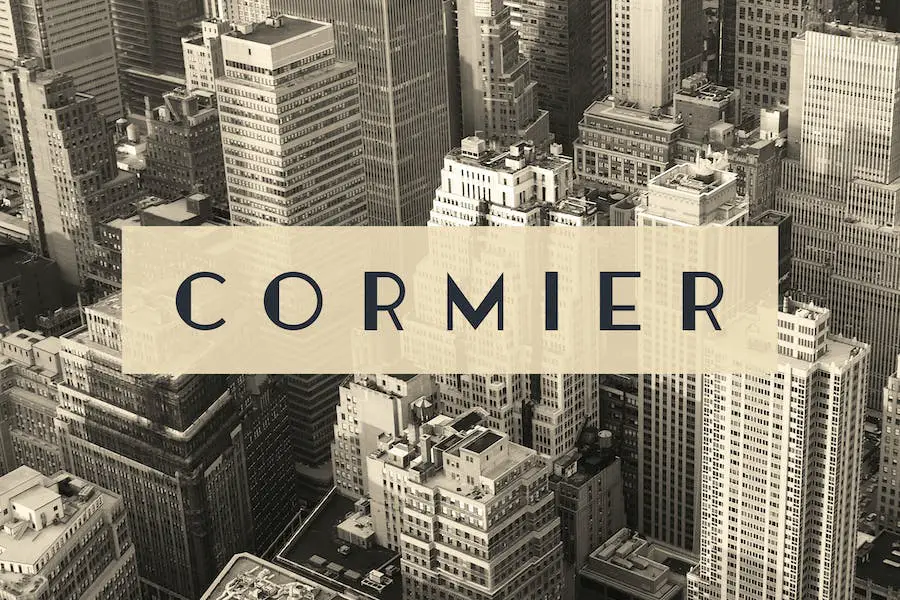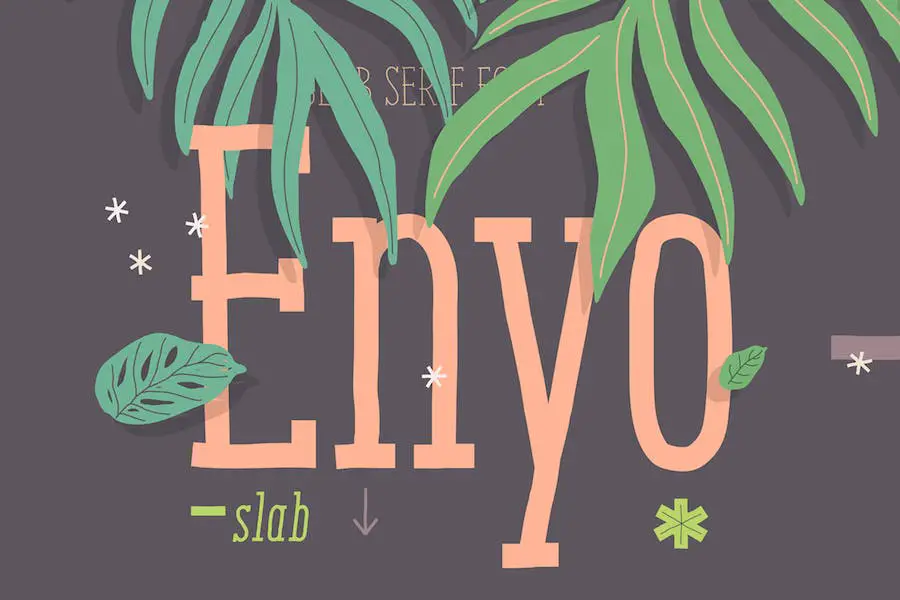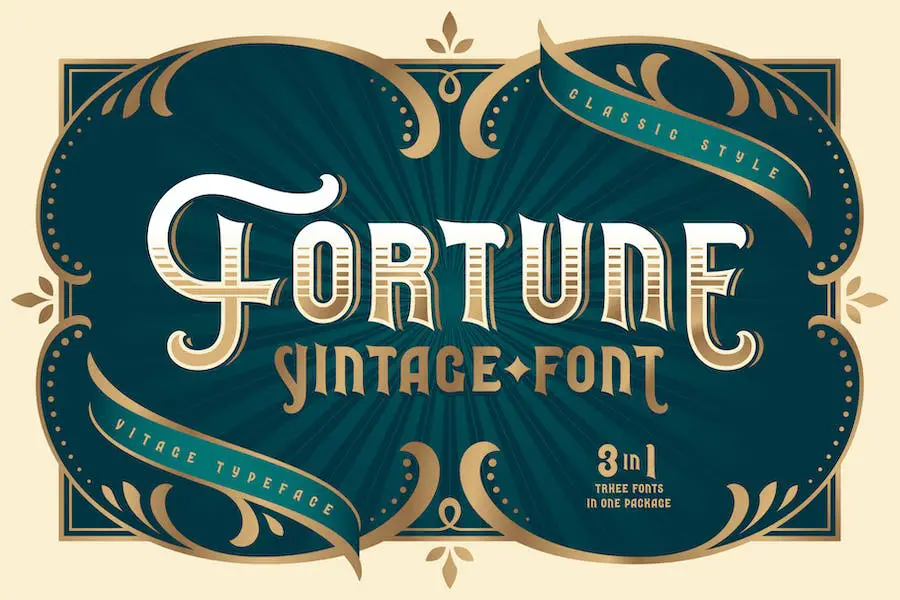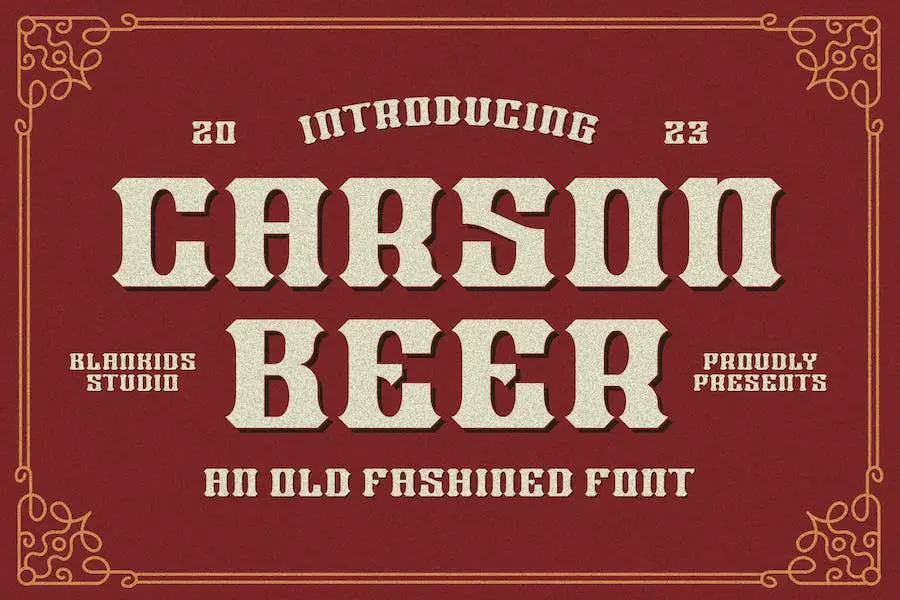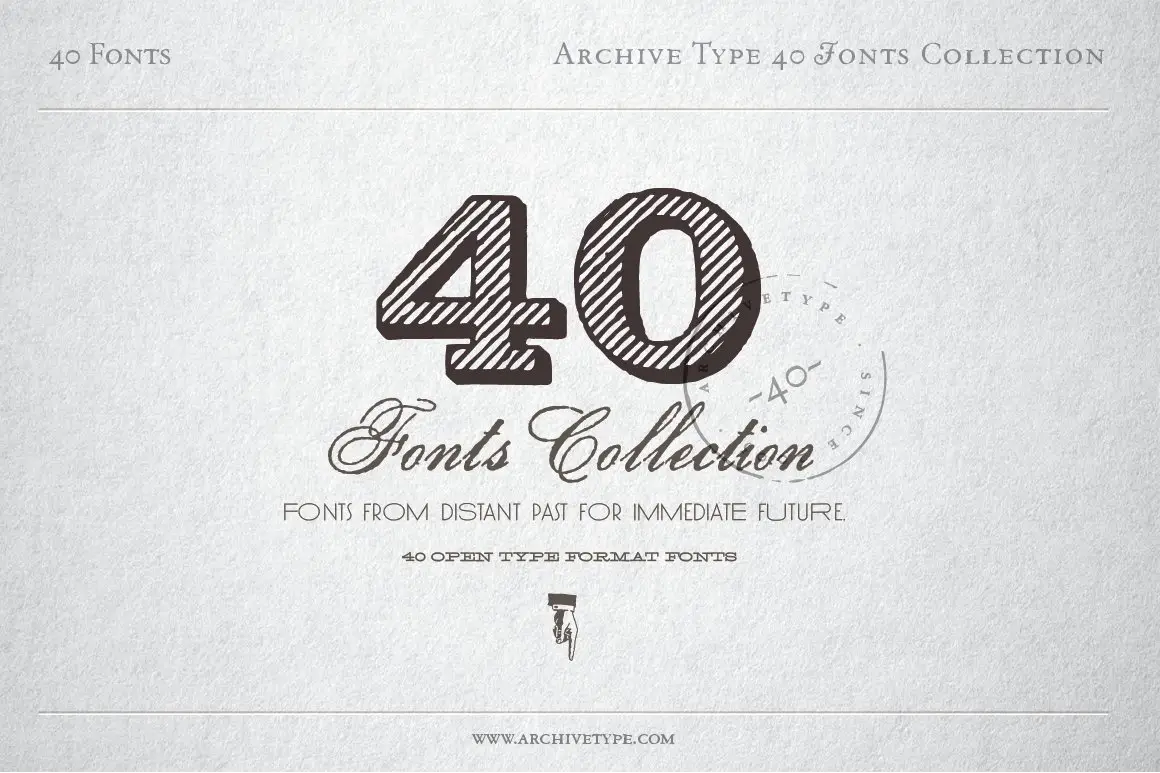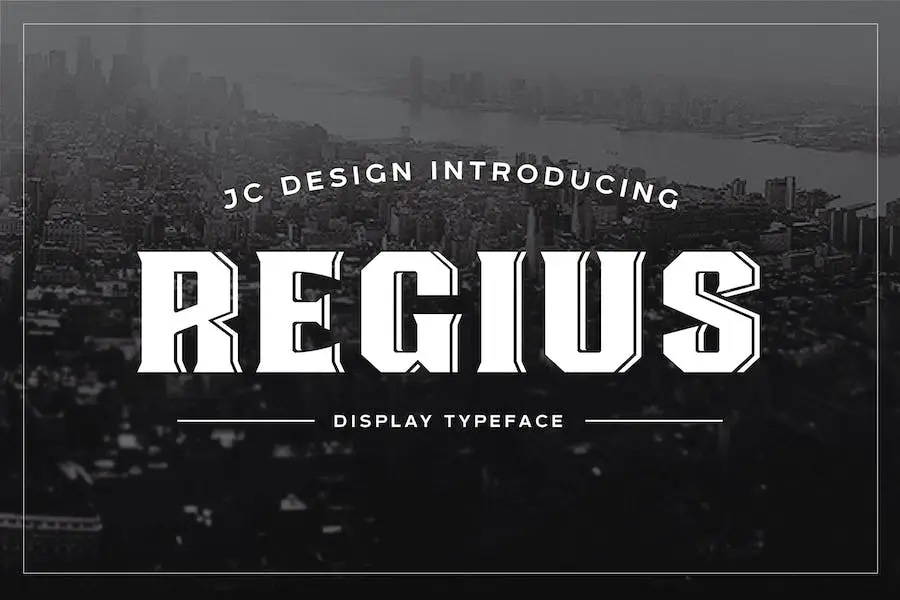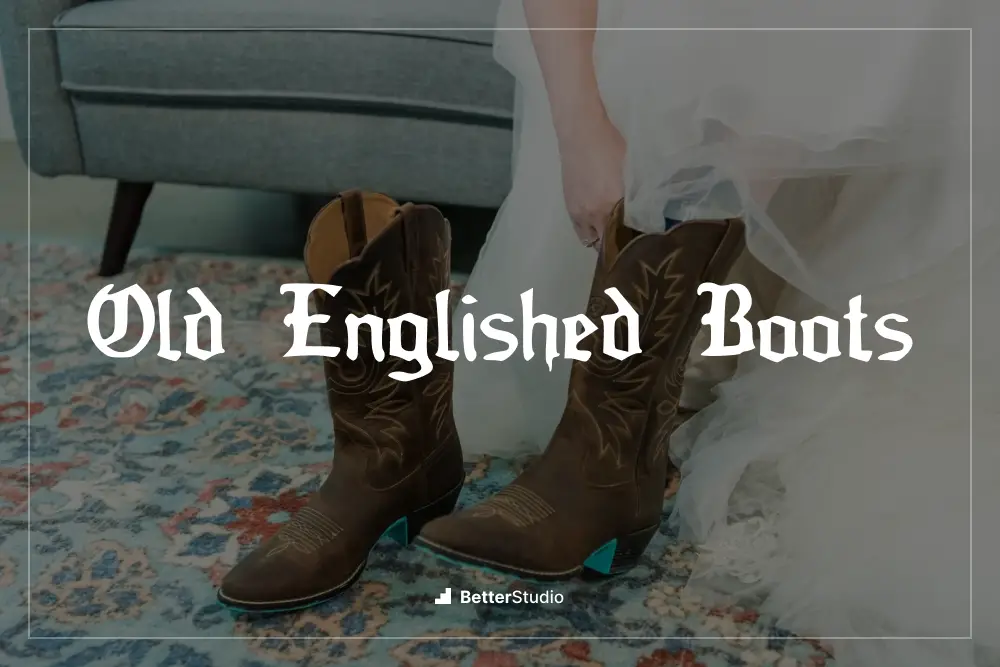
24 najlepsze staroangielskie czcionki ️ 2023 (bezpłatne i premium)
Opublikowany: 2023-05-21Czy jesteś grafikiem i szukasz idealnej starej angielskiej czcionki, aby ulepszyć projekt swojego projektu? Nie szukaj dalej! W tym artykule zebraliśmy listę 24 najlepszych starych angielskich czcionek, które z pewnością zrobią wrażenie.
Ponieważ typografia odgrywa istotną rolę w projektowaniu graficznym, wybór odpowiedniej czcionki może być trudny. Przy tak wielu dostępnych opcjach łatwo się zgubić. Dlatego przeprowadziliśmy dla Ciebie badania.
Nasz proces selekcji był obszerny i ocenialiśmy każdą czcionkę na podstawie kryteriów, takich jak popularność, wszechstronność i czytelność. Ten artykuł zawiera obszerny przewodnik po najlepszych starych czcionkach angielskich dostępnych obecnie.
W tym artykule przedstawimy Ci 24 najlepsze stare angielskie czcionki, które idealnie nadają się do każdego projektu. Niezależnie od tego, czy tworzysz logo, plakat czy projekt strony internetowej, nasza starannie dobrana oferta zapewni Ci wszystko.
Tak więc, bez zbędnych ceregieli, zanurzmy się w świat starych angielskich czcionek i znajdźmy idealną czcionkę do następnego projektu.
Najlepsze staroangielskie czcionki premium
Szukasz wysokiej jakości czcionek staroangielskich, które uatrakcyjnią Twoje projekty? Sprawdź nasze najlepsze typy, aby znaleźć najlepsze dostępne opcje premium. Nie przegap tych niezbędnych czcionek w zestawie narzędzi każdego grafika.
Wicked Olde English
Wicked Olde English to kolekcja staroangielskich czcionek Google, które są idealne dla grafików, którzy chcą dodać swoim projektom odrobinę uroku starego świata.
Te czcionki są idealne do tworzenia unikalnych i przyciągających wzrok projektów, od logo i wizytówek po plakaty i grafikę do mediów społecznościowych.
Starożytny
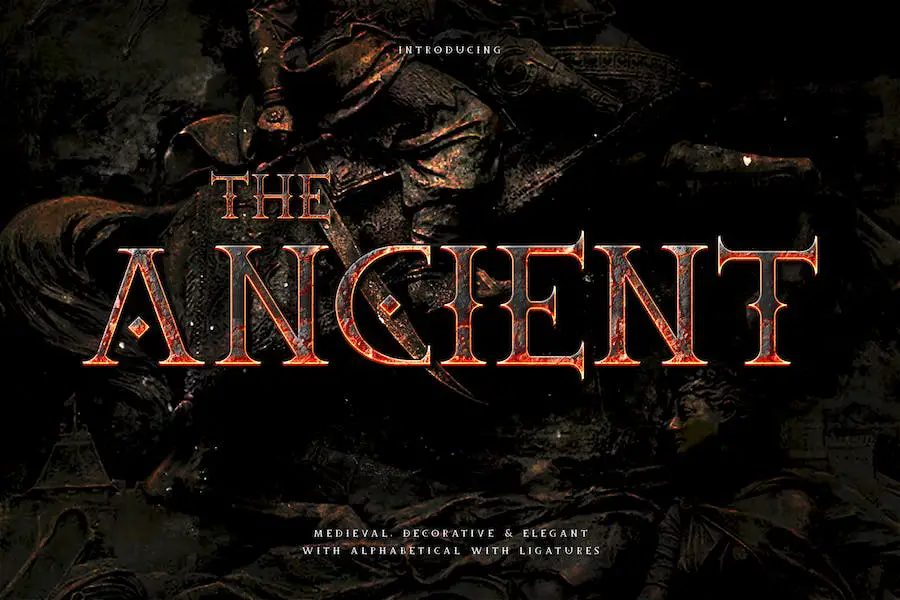
The Ancient to średniowieczna czcionka bez, która nadaje Twojemu projektowi styl vintage. To doskonały wybór dla grafików, którzy tworzą zaproszenia, banery, tytuły filmów, marki, wydarzenia, gry i nie tylko.
Jeśli szukasz czcionki, która pomoże Ci osiągnąć średniowieczną estetykę, The Ancient może być dla Ciebie idealną opcją.
Lore Nekromantea Hollow
Lore Nekromantea Hollow to piękna odręczna czcionka staroangielska, która została zaprojektowana do użytku w przeszłych, obecnych i przyszłych książkach, takich jak Tomy, Biblie i Grimoires.
Ta czcionka jest dostępna w 3 wariantach x 2 (zwykły i pusty) z różnymi dużymi literami: Nokturnia, Pandemonia i Nekromantea. Puste wersje mają celowo nierówną pracę linii i więcej punktów kontrolnych, dzięki czemu idealnie nadają się do nagłówków i wyświetlanego tekstu.
W przypadku nagłówków i wyświetlanego tekstu ta czcionka przyciągnie uwagę czytelników i doda odrobinę wyrafinowania Twojemu projektowi. Ogólnie rzecz biorąc, jeśli szukasz staroangielskich czcionek do programu Word, Lore Nekromantea Hollow to świetny wybór, który zapewnia wszechstronność i piękno w równym stopniu.
Chervels w starym stylu
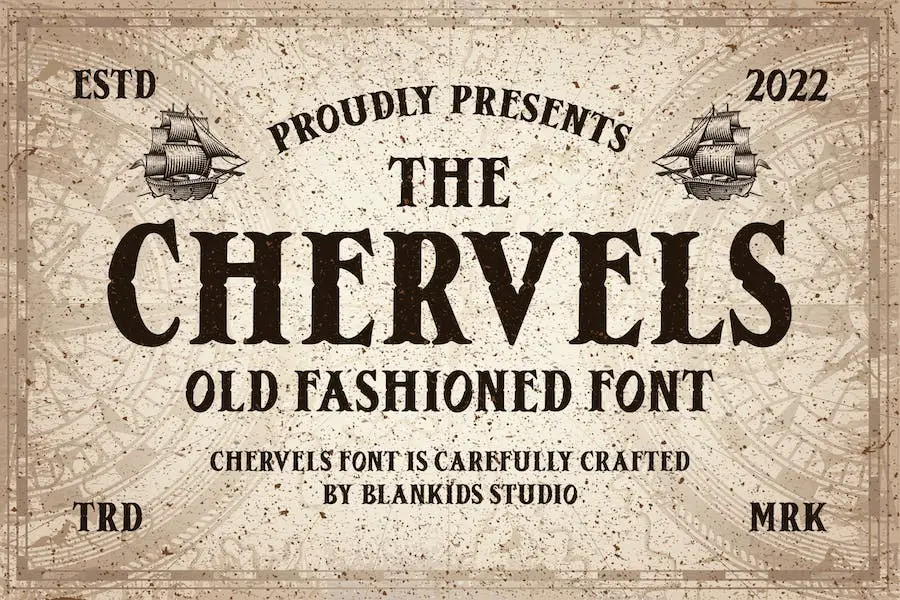
Chervels an old Fashioned to czcionka inspirowana stylem vintage, która dodaje figlarnego charakteru każdemu projektowi. Dzięki pięknie wykonanej estetyce ta czcionka jest idealnym wyborem do okładek książek, plakatów, opakowań, towarów, logo i nie tylko.
Czcionka Chervels, staroangielska, jest idealna do wykorzystania w projektach Canva, które wymagają czcionki staroangielskiej. Jest łatwy w użyciu i można go zastosować do różnych elementów projektu. Niezależnie od tego, czy projektujesz plakat, czy tworzysz logo, ta czcionka pomoże Ci osiągnąć pożądany styl vintage.
Blond
Blonde to nowoczesna rodzina czcionek typu blackletter, która obejmuje dwa style: ozdobną szeryfową teksturę i bezpłatną rotundę sans. Wyróżnia się na tle tradycyjnych staroangielskich czcionek opływowym wyglądem i stylem, zachowując jednocześnie stylizowane i czytelne cechy tego gatunku.
Ta rodzina czcionek wykorzystuje kąt obrysu 50° i zaokrąglone elementy, co nadaje jej wyjątkowy, organiczny wygląd.
Ogólnie rzecz biorąc, Blonde to świetny wybór dla każdego, kto szuka nowoczesnego podejścia do staroangielskich czcionek do projektów obwodów. Jego unikalny design i czytelność sprawiają, że jest to wyjątkowa opcja dla projektantów, którzy chcą przekazać poczucie tradycji i elegancji w swojej pracy.
Oryginały
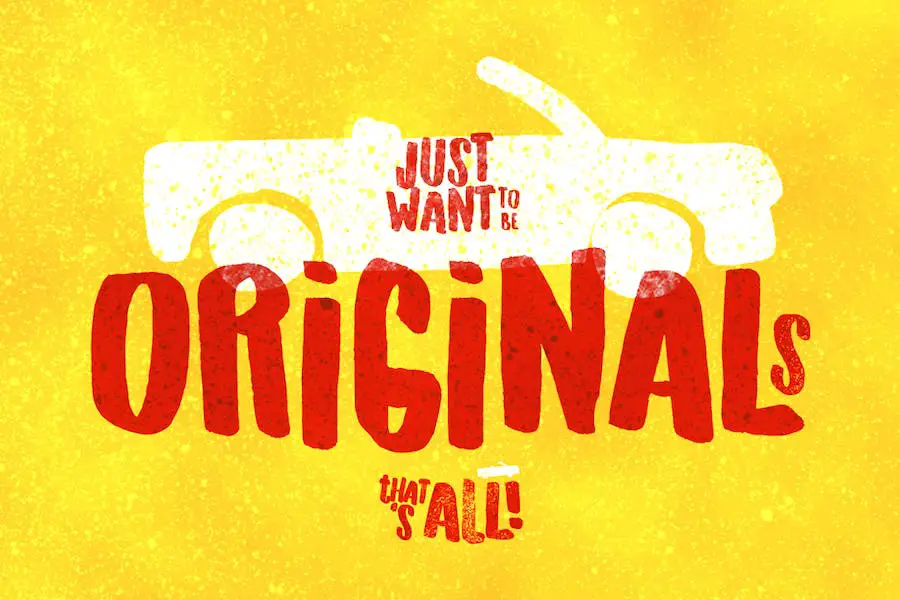
Originals to ręcznie rysowana, zabawna czcionka wyświetlana, która może nadać Twoim projektom niepowtarzalny charakter. Ten krój pisma doskonale nadaje się do nadruków na szyldach, koszulkach lub kartach i najlepiej sprawdza się w przypadku projektów o tematyce letniej. Jeśli szukasz czegoś świeżego i zabawnego, warto spróbować Originals.